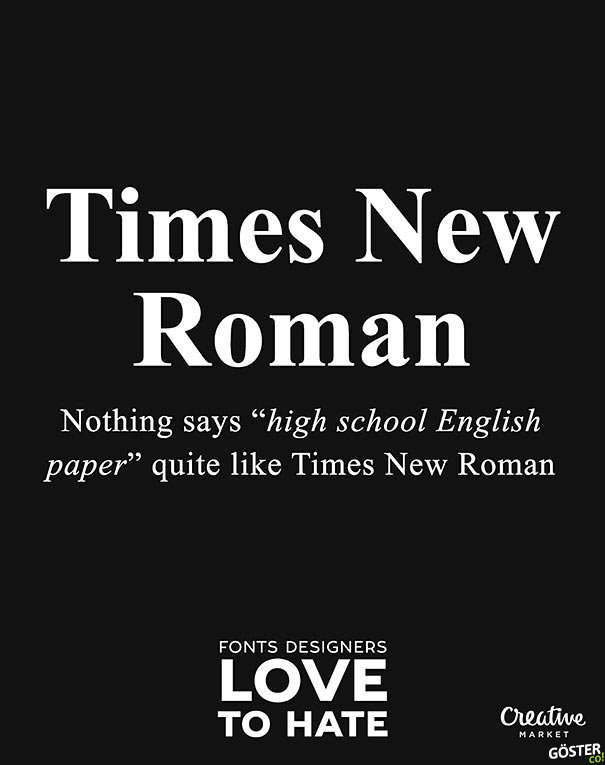
İnsanların Nefret Etmekten Keyif Aldığı 11 Yazı Tipi
Times New Roman: Liselerdeki ders notu fontu. Biri hocaya Word’de başka fontlar olduğunu hatırlatsın.